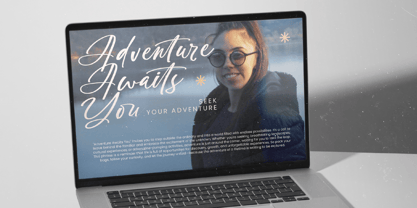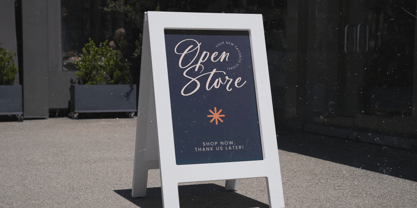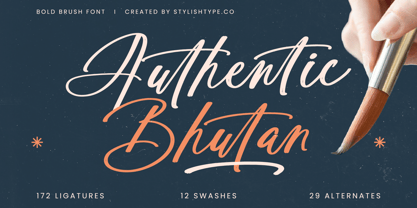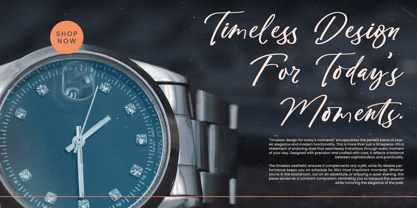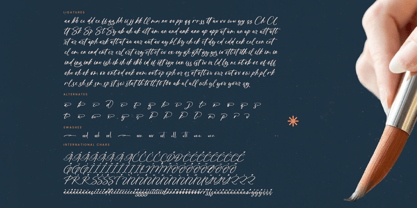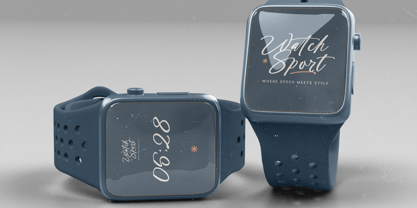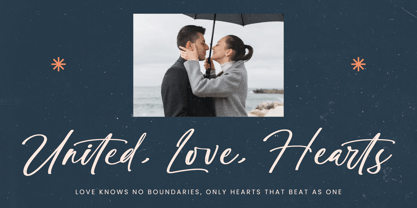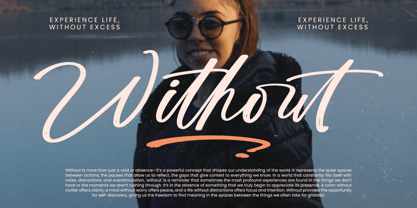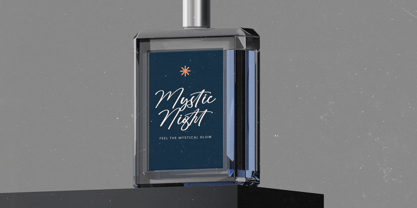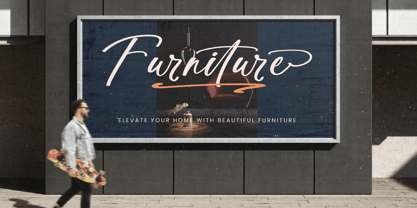
Authentic Bhutan
por Stylishtype Studio
La familia tipográfica Authentic Bhutan fue diseñada por Heru Utama Putra y publicada por Stylishtype Studio. Authentic Bhutan contiene 2 estilos y opciones de paquete familiar. Más información sobre esta familia
Authentic Bhutan - Bold Brush Font , from Stylishtype, Suitable for any projects such as: logos, branding projects, homeware designs, product packaging, mugs, quotes, posters, shopping bags, t-shirts, book covers, name card, invitation cards, greeting cards, label, photography, watermark, special events, and all your other luxury and beautiful projects that need a Luxury Script taste.
Diseñadores: Heru Utama Putra
Fundición actual: Stylishtype Studio